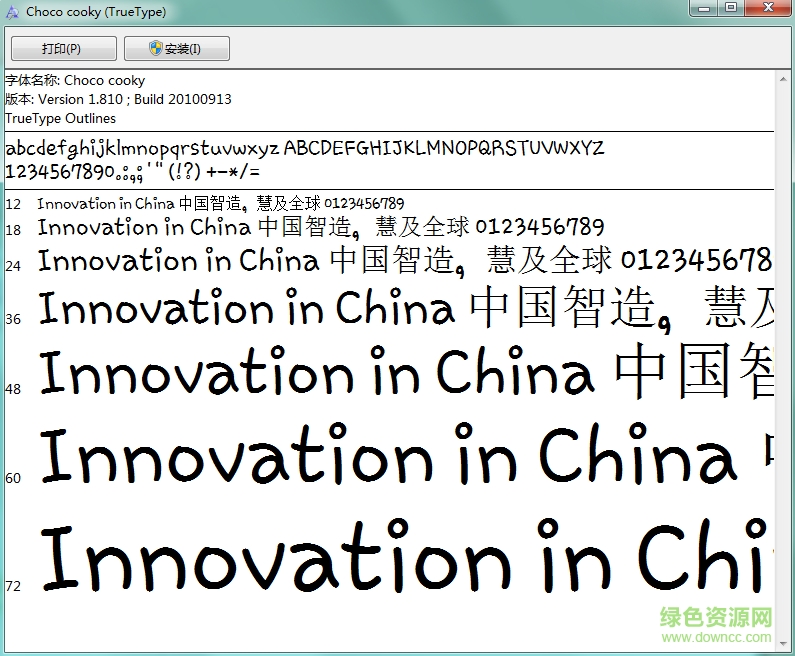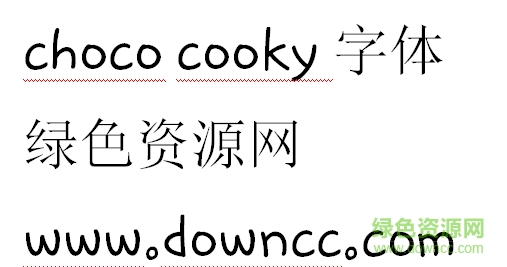
choco cooky ttf是一款造型充滿童趣的藝術(shù)字體,圓潤的外觀的清晰的辨識度讓你的閱讀體驗(yàn)更加,無論是平面設(shè)計(jì)還是海報(bào)制作都很有特色,綠色資源網(wǎng)誠意推薦!
choco cooky字體,字跡簡約清秀,充滿孩子的天真活潑感,有著卡通字體的趣味,字體連貫不拖沓,給人舒適的視覺呈現(xiàn),可運(yùn)用于藝術(shù)創(chuàng)作、文字編輯、排版印刷等領(lǐng)域!